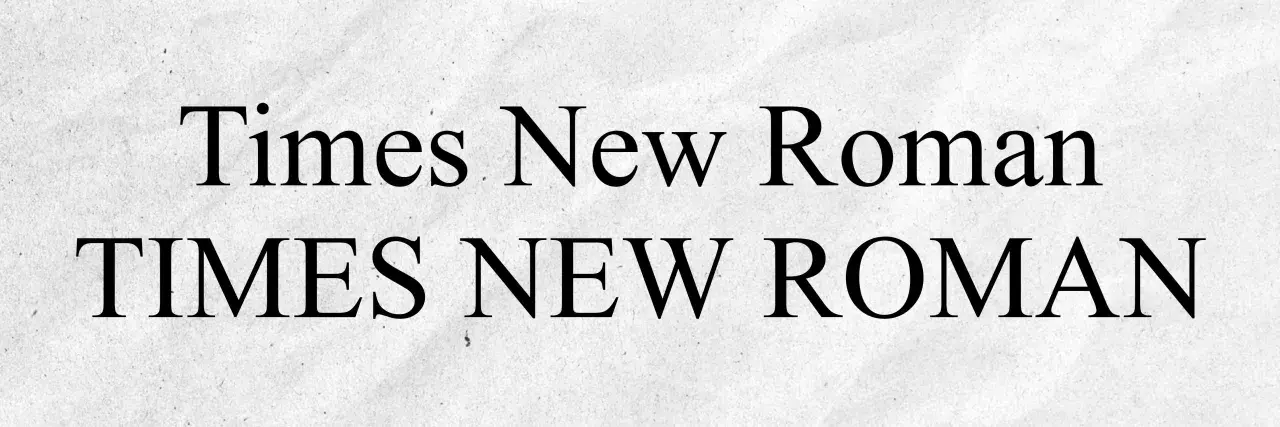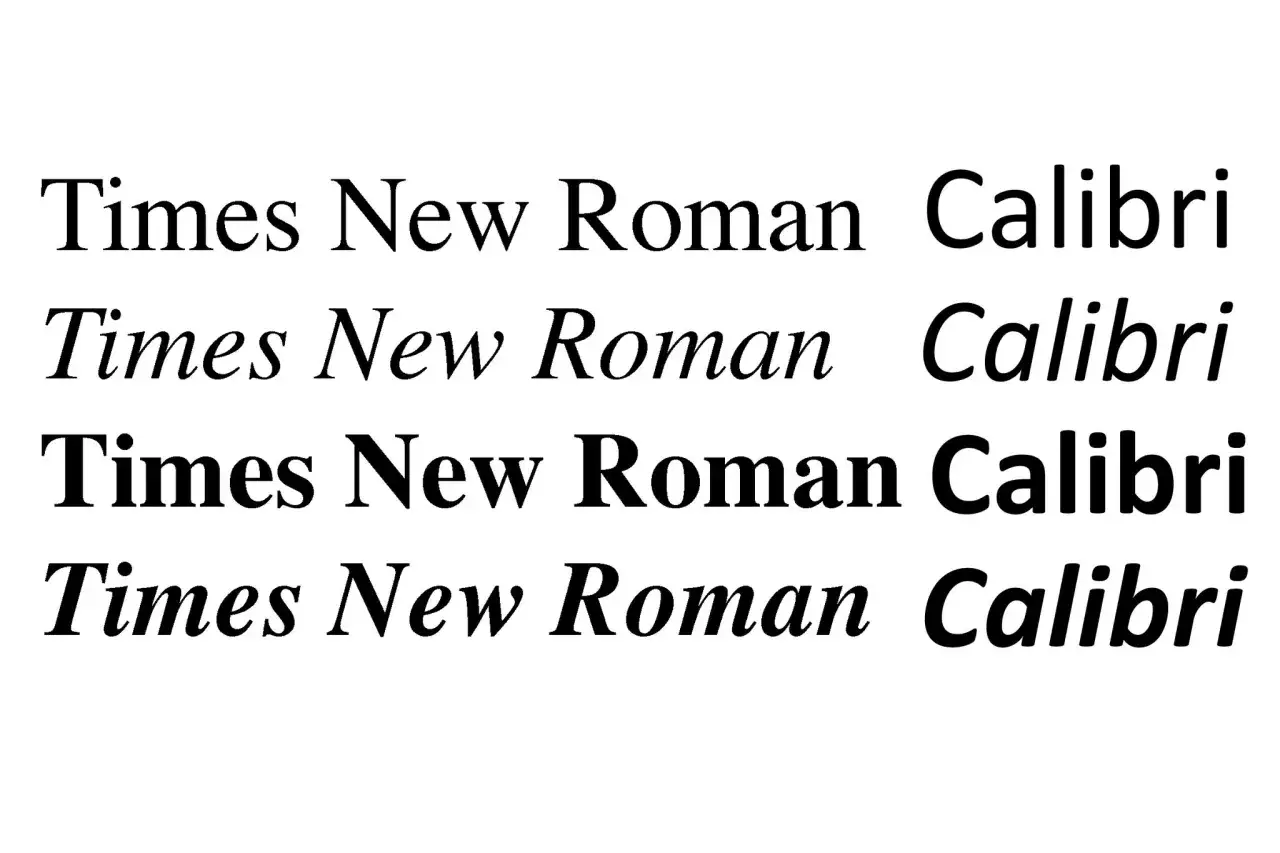
Czcionka do dokumentów - Jak wybrać? Times New Roman, Arial
Times New Roman, klasyczna czcionka, idealna do dokumentów. Wersja z wielkimi literami podkreśla jej elegancję.
W oficjalnym dokumencie czcionka nie jest ozdobą, tylko narzędziem. Od niej zależy, czy pismo wygląda profesjonalnie, czy da się je wygodnie czytać na ekranie i czy nie zderzysz się z wymaganiami urzędu, uczelni albo firmy. Gdy pojawia się pytanie, jaką czcionką pisać dokumenty, najbezpieczniej myśleć nie o „najładniejszym” kroju, ale o takim, który jest prosty, znany i dopasowany do formy dokumentu.
Najbezpieczniejszy wybór to prosty krój, czytelny rozmiar i spójny układ
• Jeśli nie masz wytycznych, w dokumentach drukowanych najbezpieczniej wypada Times New Roman 12 pt.
• Do dokumentów ekranowych i formularzy lepiej sprawdzają się Arial, Calibri lub Aptos.
• W oficjalnych pismach ważniejsza od „ładnej” czcionki jest czytelność, odstępy i konsekwencja formatowania.
• Unikaj ozdobnych krojów, mieszania kilku fontów i schodzenia poniżej 11-12 pt.
• Jeśli instytucja ma własny szablon, trzymaj się go bez kombinowania.
Co naprawdę decyduje o wyborze kroju
Nie zaczynam od nazwy fontu, tylko od tego, gdzie dokument będzie czytany. Inaczej projektuje się pismo do urzędu, inaczej raport na ekranie, a jeszcze inaczej załącznik, który ktoś później wydrukuje i włoży do akt. W praktyce o wyborze decydują cztery rzeczy: medium, odbiorca, długość tekstu i to, czy dokument ma wyglądać bardziej tradycyjnie, czy nowocześnie.
Jeśli papier ma wyjść z drukarki i trafić do teczki, zwykle lepiej działa krój bardziej formalny. Jeśli plik będzie czytany na monitorze, priorytetem staje się prostota liter, wyraźne różnice między znakami i brak zbędnych ozdobników. Ja patrzę też na to, ile miejsca tekst zajmuje na stronie, bo to często przesądza o wygodzie czytania bardziej niż sama marka fontu.
• Druk zwykle lepiej znosi kroje szeryfowe, bo dają wrażenie porządku i stabilności.
• Ekran częściej lepiej obsługują fonty bezszeryfowe, zwłaszcza w dłuższych dokumentach PDF.
• Odbiorca ma znaczenie, bo urząd, klient i komisja nie oczekują dokładnie tego samego stylu.
• Charakter treści też ma wagę: formalne pismo wymaga innej dyscypliny niż instrukcja czy raport.
To właśnie dlatego sam wybór kroju ma sens dopiero wtedy, gdy dopasuję go do formy dokumentu. A wtedy od razu widać, które fonty naprawdę są bezpieczne, a które tylko wyglądają „profesjonalnie” na pierwszy rzut oka.
Porównanie czcionek: Times New Roman i Calibri w różnych stylach. Wybór odpowiedniej czcionki, np. jaką czcionką pisać dokumenty, zależy od celu.
Najbezpieczniejsze kroje do dokumentów oficjalnych
Jeśli chcesz prostego wyboru bez ryzyka, nie potrzebujesz dziesięciu wariantów. W praktyce kilka krojów wraca najczęściej, bo po prostu dobrze działa w obiegu urzędowym i biurowym. Microsoft Learn opisuje Aptos jako nowoczesny krój bezszeryfowy zaprojektowany z myślą o czytelności, więc dobrze wpisuje się w nowsze szablony dokumentów. Reszta stawki też jest przewidywalna, a to w oficjalnym piśmie bywa cenniejsze niż oryginalność.
Krój Typ Najlepsze zastosowanie Mój komentarz
Times New Roman Szeryfowy Pisma urzędowe, formalne wydruki, załączniki Najbardziej „urzędowy” wybór. Bezpieczny, jeśli nie chcesz dyskutować o estetyce.
Arial Bezszeryfowy Dokumenty cyfrowe, formularze, raporty, CV Neutralny i bardzo czytelny na ekranie. Dobry, gdy dokument ma żyć głównie w PDF-ie.
Calibri Bezszeryfowy Korespondencja biurowa, oferty, notatki, dokumenty wewnętrzne Miękki i nowoczesny, ale nadal zachowuje oficjalny charakter.
Aptos Bezszeryfowy Nowe szablony Office, współczesne dokumenty Daje świeży, czysty efekt i dobrze sprawdza się tam, gdzie nie potrzebujesz klasycznej oprawy.
Georgia Szeryfowy Raporty, dłuższe teksty do druku, materiały redakcyjne Bardziej elegancka niż Times New Roman, ale mniej „urzędowa”.
Verdana Bezszeryfowy Dokumenty ekranowe, materiały pomocnicze, instrukcje Świetna czytelność, choć zajmuje sporo miejsca na stronie.
Gdybym miał wskazać jeden wniosek, powiedziałbym tak: Times New Roman wygrywa formalnością, a Arial, Calibri i Aptos wygrywają wygodą na ekranie. Wybór nie jest więc kwestią gustu, tylko tego, co ma dominować w odbiorze dokumentu: tradycja czy czytelność cyfrowa. I właśnie tu najlepiej widać różnicę między krojem szeryfowym a bezszeryfowym.
W kolejnej sekcji rozbijam to na prosty praktyczny podział, bo w oficjalnych pismach ta decyzja naprawdę robi różnicę.
Szeryfowa czy bezszeryfowa czcionka
Szeryfowe kroje, takie jak Times New Roman czy Georgia, kojarzą się z dokumentem bardziej formalnym, książkowym i uporządkowanym. Dobrze pracują w dłuższym tekście drukowanym, bo nadają mu stabilny rytm i wizualnie „kotwiczą” linie. Jeśli dokument ma wyglądać klasycznie, szeryfowy font jest zwykle bezpieczniejszym wyborem.